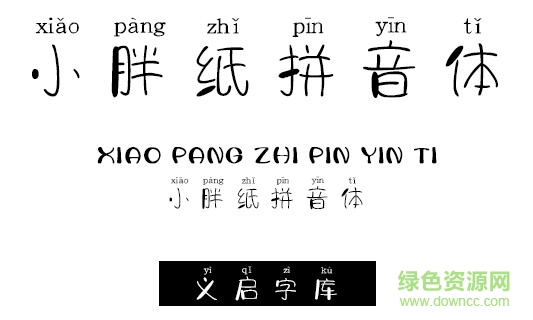
義啟小胖紙拼音體是一款非??蓯鄣?a href="http://m.lz0519.com/k/yishuziti/" target="_blank">藝術(shù)字體,這款字體應(yīng)用十分廣泛,海報(bào)宣傳、廣告設(shè)計(jì)、排版印刷都可以使用,喜歡這款字體的朋友可以來綠色資源網(wǎng)下載體驗(yàn)!
哇!你又喝奶茶又吃炸雞!不怕胖嗎?我會瘦的我只是先胖著玩玩!